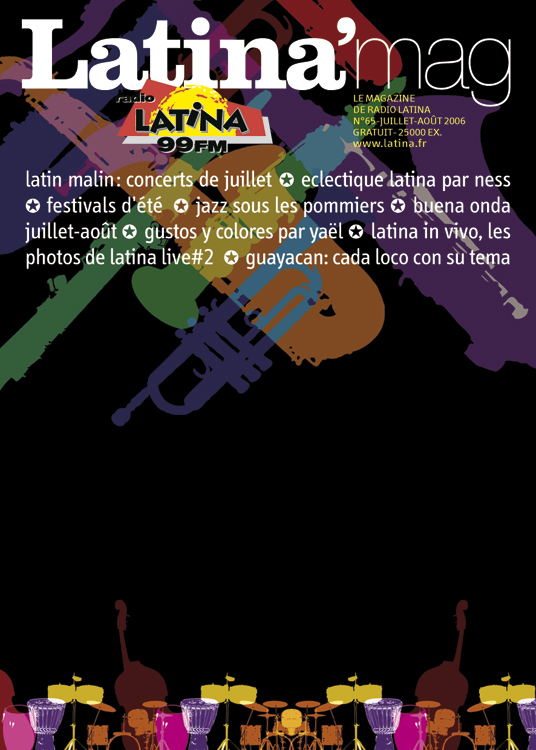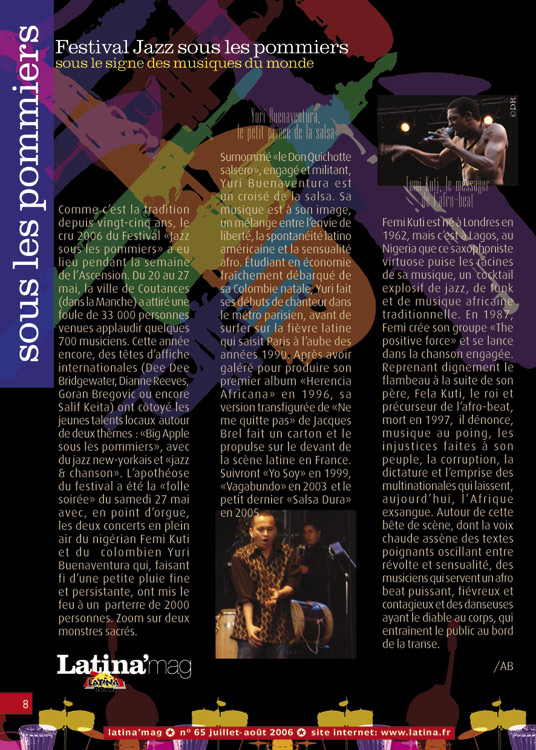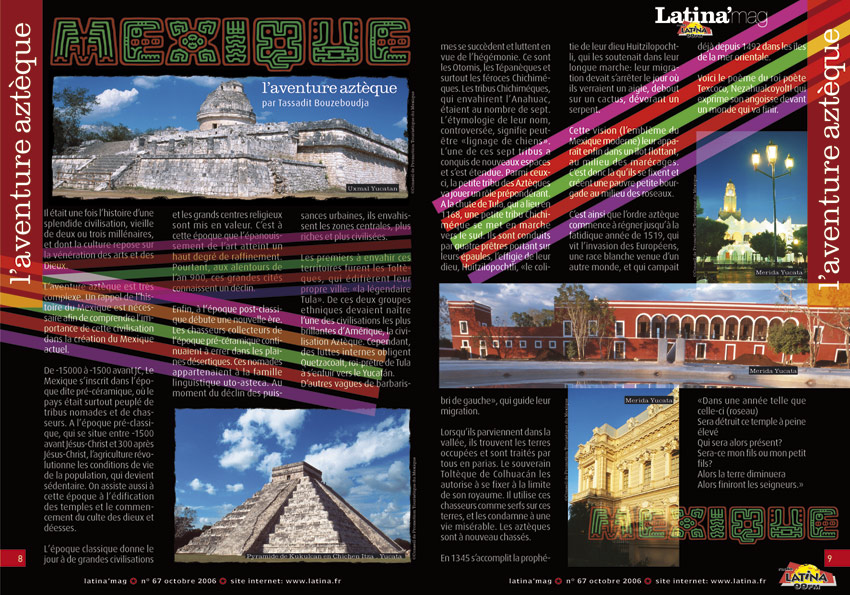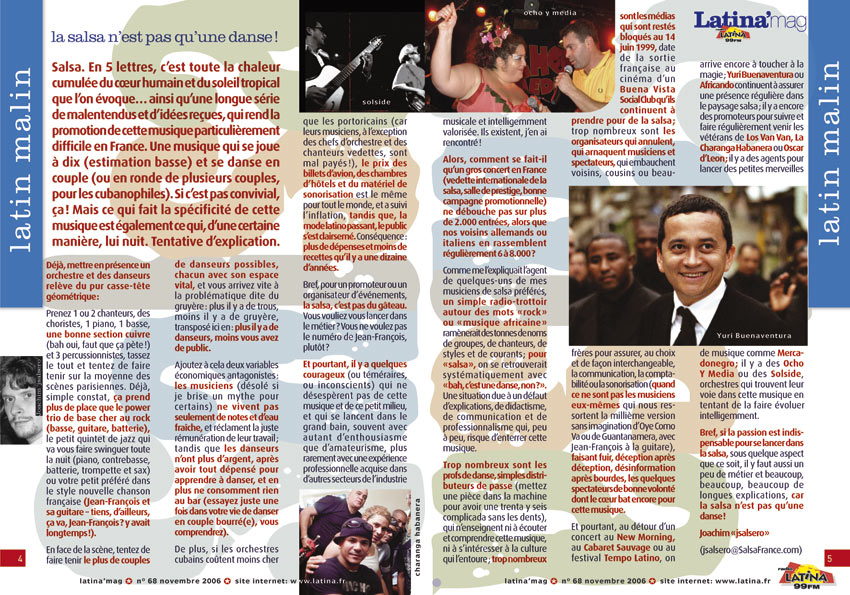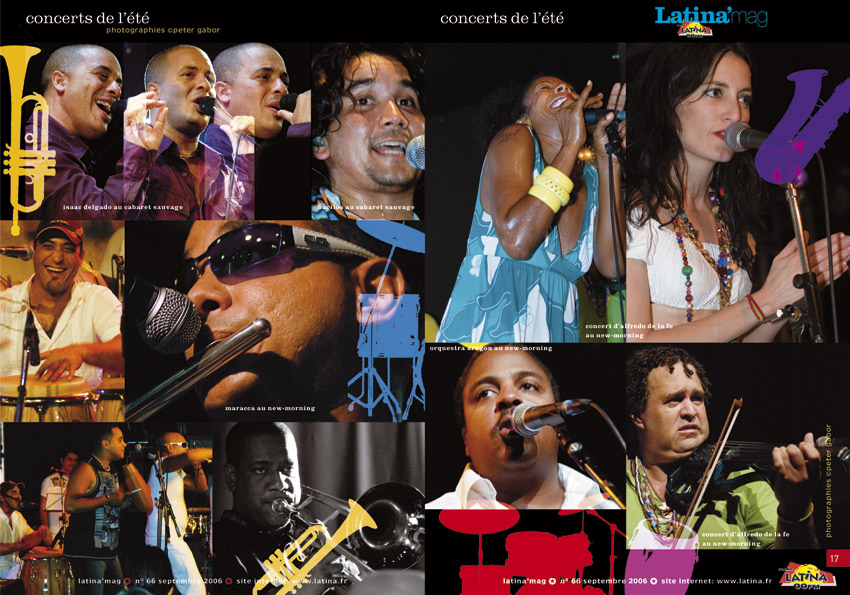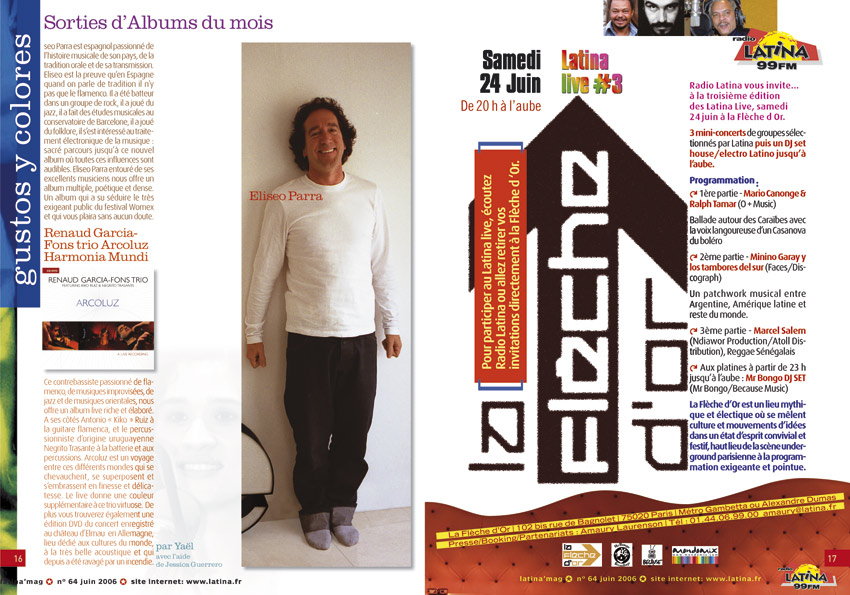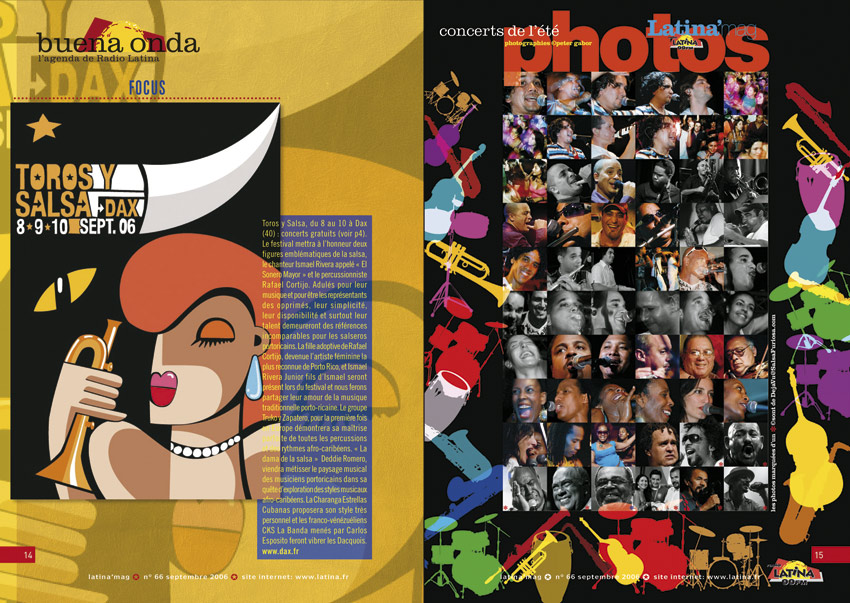
Radio Latina arrête son magazine | Typographie d’un Magazine de Musique World
Voici un digest de mes plus belles pages que j’ai conçu pour Radio Latina. Une occasion pour votre serviteur d’expérimenter d’autres champs graphiques que les rapports financiers ou la presse d’entreprise. Une opportunité également de revisiter la photographie de scène pour laquelle je me suis pris de passion comme vous avez pu vous en rendre compte. Pourquoi Radio Latina a-t-elle arrêté Latina Mag. Un de ces exemples de la perversion du système capitaliste que j’aborrhe. Fin 2006, le groupe Start se porte acquéreur de la Radio. Comprenez par là d’une fréquence FM (99FM). Ils présentent le dossier au CSA qui les retoquent une première fois pour des raisons évidentes. Plus rien de l’objet culturel qui était couché dans le dossier historique de la Radio n’y figurait. Il faut bien comprendre qu’au delà des grandes fréquences nationales ou des NRJ et itou, il y a une flopée de petites fréquences dont l’audience oscille entre 1 et 3% de part de marché. Le groupe Start possède déjà quelques petites fréquences et cela lui permet de faire tourner une régie publicitaire. À la deuxième présentation du dossier en décembre (eh oui le CSA autorise le repêchage) l’autorité de régulation a accepté le projet…
Le calcul est simple. Peu importe le contenu de l’antenne, peu importe que l’audience chute de 1,8% à 0,5 ou 0,9% pourvu qu’ils réussissent à couper les dépenses de façon radicale (on installe l’antenne dans un bureau climatisé, quelques robots pour débiter une musique au kilomètre) et le tour est joué. Pourquoi continuer à sponsoriser des showcases , à faire se rencontrer des musiciens, à lancer des artistes comme Raul Paz qui sans Radio Latina n’aurait sans doute jamais percé. Je songe à tous les afficionados de cette musique qui voyaient déjà les concerts cubains et sud-américains diminuer dangereusement à Paris. Je songe à tous les Maraca, Tito Puentes et autres grands artistes comme Henri Guedon qui ont pu se produire, se distribuer, se faire connaître grâce à une poignée d’animateurs chevronnés qui ne ménageaient ni leur temps ni leurs efforts. Passionnés vous dis-je, nous l’étions tous. J’espère me tromper, j’espère sincèrement que les nouveaux propriétaires vont se ressaisir et comprendre qu’ils ont racheté là une de ces exceptions culturelles dont nous sommes tant fiers en France. Et vive la fête de la musique.
Henri Guedon, au New Morning, peu de temps avant sa disparition.
Pour la typographie et la mise en page, je devrais plutôt dire la mise en scène, j’avais fait une étude bench_mark de tous les magazines de musique, de la world au rock en passant par les mag Hip-Hop et Jazz. Essayé de créer une ambiance chaude tout en respectant quelques valeurs auxquelles je reste très attaché. La lisibilité, la hiérarchie, les appels de lecture… etc. Pratiqué la mise en couleur des textes pour rendre vivant des quantités de textes que personne n’aurait sans doute lu, pour rythmer la lecture et faire voyager le regard des amateurs de cette musique vivante. Je n’ai pas eu de gros souci de repérage sur ces textes pour la raison que l’imprimeur m’a accordé la trame 175 et son calage électronique était parfait. Sans aucun débord. Relooké aussi le logotype du magazine avec un puissant Clarendon qui rompait avec les caractères fantaisies qui foisonnent dans tous les flyers immondes qui gravitent autour de ce petit monde. Bref, j’ai essayé de répondre à cette question: est-il possible d’aborder les musiques du Monde avec l’œil exigeant d’un graphiste qui n’aime pas trop le manque de rigueur, tout en respectant une autre exigeance, celle d’une presse qui se veut musicale, séductrice, consensuelle et cherche la proximité avec ses lecteurs. Une presse qui fait référence aux cultures du sud. Pas simple. J’en profite pour remercier Anaïs la rédactrice en chef d’avoir permis de garder une feuille de route graphique malgré les pressions du bocal. Les gens de Radio n’ont jamais été très sensible au Print ;-) Mais je vous laisse librement commenter le sujet. Curieux de vos avis.
La moitié basse de la couv était vendu par la pub. Comment intégrer chaque mois une pub parfois horrible avec une couverture qui se voulait élégante, sans détruire toute l’ambiance.
Bien sûr, j’aurais préféré pouvoir disposer de pleines pages pour les focus sur les grands artistes. Mais la pagination ne le permettait pas. D’où la nécessité de jongler en permanance avec des légendes qui viennent superposer les images.
Cette page occupait quatre pages quand j’ai repris la maquette initiale. L’enjeu était donc de taille. Mais grâce à une typographie bien adaptée, le Galfra que Ladislas Mandel m’avait confié j’ai pû recomposer cette liste «imbittable» en corps 4,5 et libérer ainsi pas mal de place pour le rédactionnel.
Comme je l’ai déjà expliqué dans des billets précédents, je suis très attaché au réglage d’un beau gris typo. Et lorsque la contrainte ultime d’un A5, s’impose à vous, l’enjeu est de taille. Réglages fins, très fins. Contrôle permanent des lézardes etc. Si j’avais opté pour le fer à gauche, perte de 15 à 20% de place pour le texte. Impossible.
Et quel plaisir lorsque je pouvais jouer avec un peu de blanc.